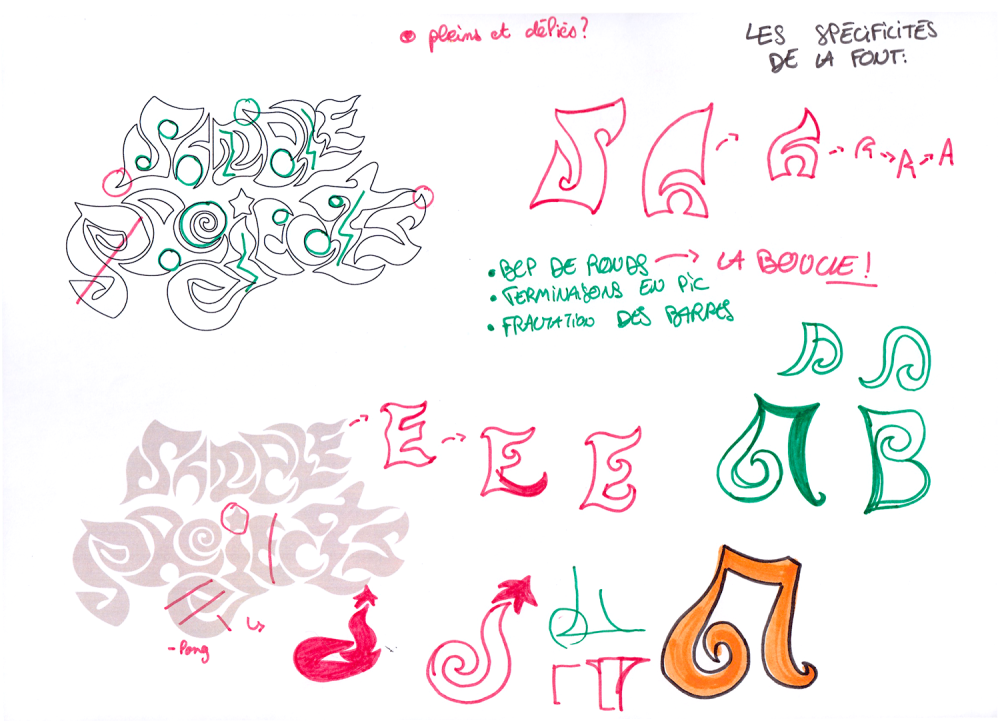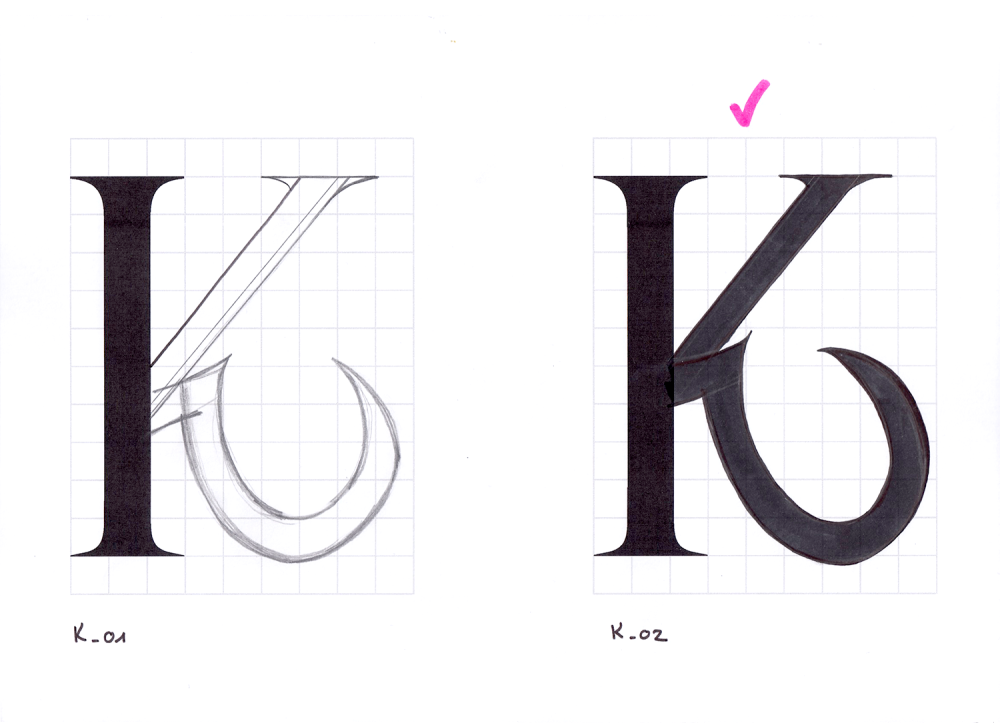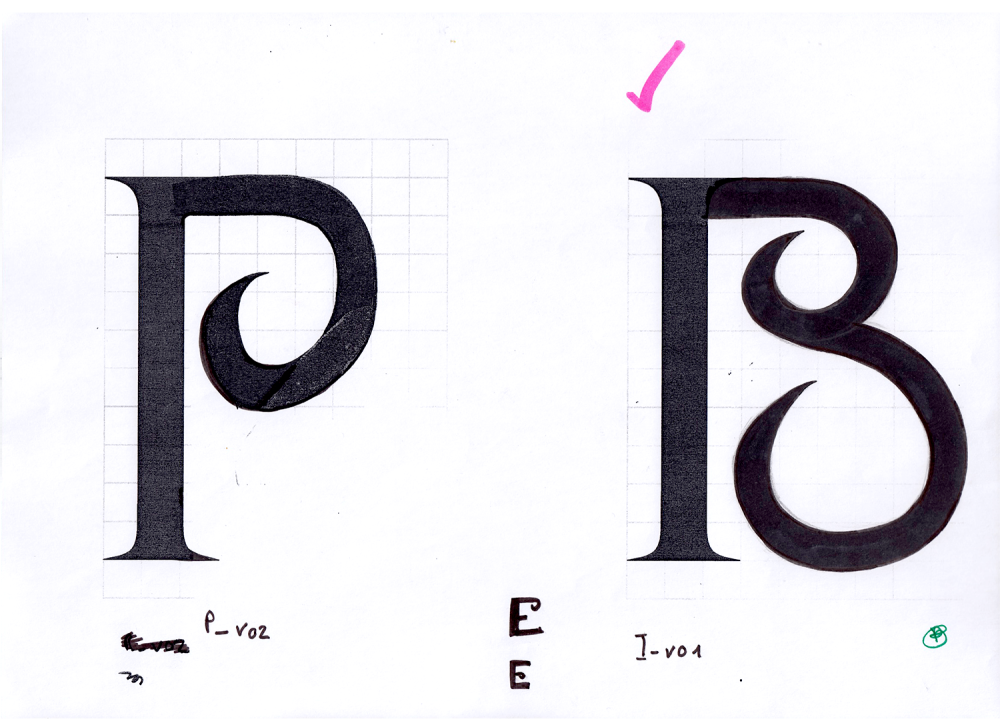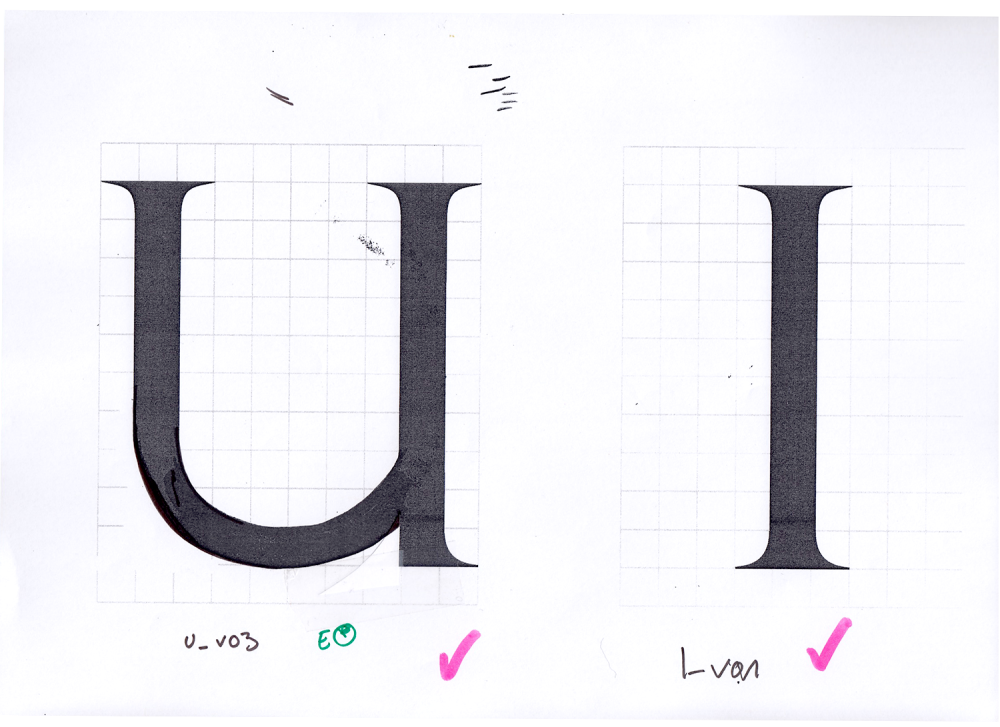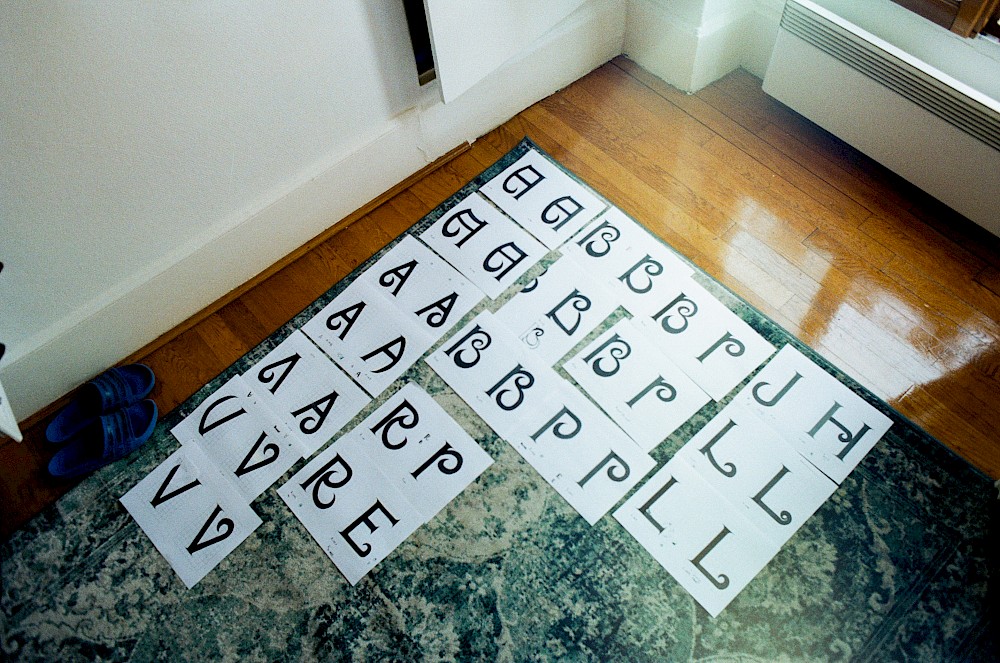
La typo est 100% faîtes à la mano, c'est qu'une vecto pour l'instant. Pour débuter je suis parti d'une grille on ne peut plus classique. J'ai commencé par dessiner les fûts. Une fois fixé, j'ai commencé le gros du dessin de la font.
p'tite photo en bombe, de toutes les lettres avec les claquettes! Pour celleux qui voudraient redessiner la font ou la compléter je peux envoyer les scans des dessins à la main 😳😳😳
En 2022, je suis toujours en stage chez Sample Projects, une marque de vêtements parisienne qui a un univers assez cryptique avec des références comme Elden Rings, Le Seigneur des Anneaux ou Le Labyrinthe de Pan. Après avoir finalisé, une première typo on me demande, cette fois-ci, de faire une custom qui sera utilisé sur les différents supports de com, étiquettes, etc. Le projet sera abandonné à une semaine de la fin du stage (ᵕ—ᴗ—)